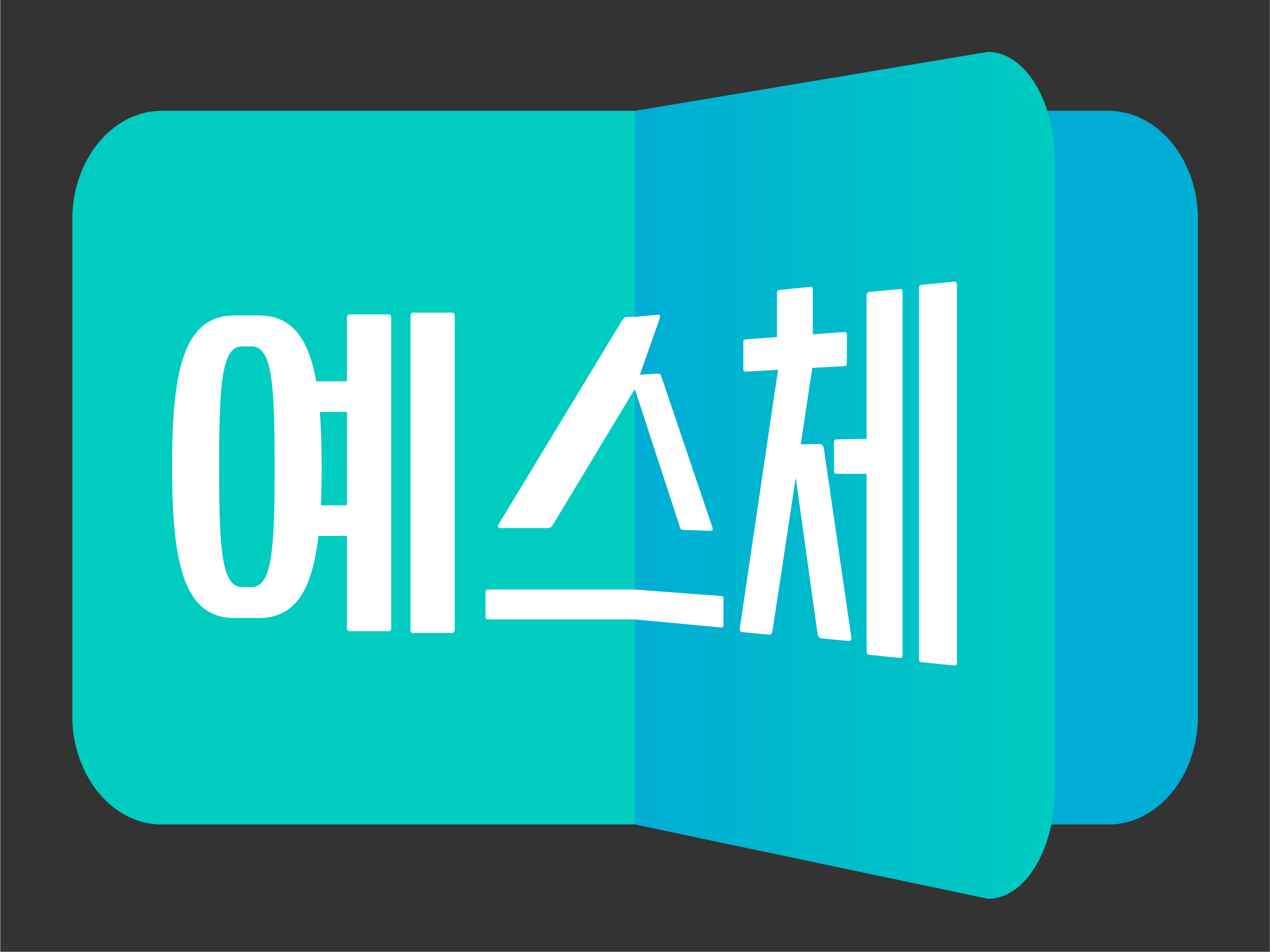
YES24 [예스고딕, 예스명조]
창립 20주년을 기념하여 다양한 감성을 아우를 수 있는 YES24만의 공간을 표현한 전용서체. YES24의 확장 이미지를 담고 있는 '햇살', '햇빛'을 그래픽 모티브로 제작한 제목용 '예스체'와 전통적 고딕, 명조의 형태를 플랫폼에 맞추어 현대적으로 재해석한 '예스 고딕', '예스 명조', 총 3가지 룩으로 제작하였다.